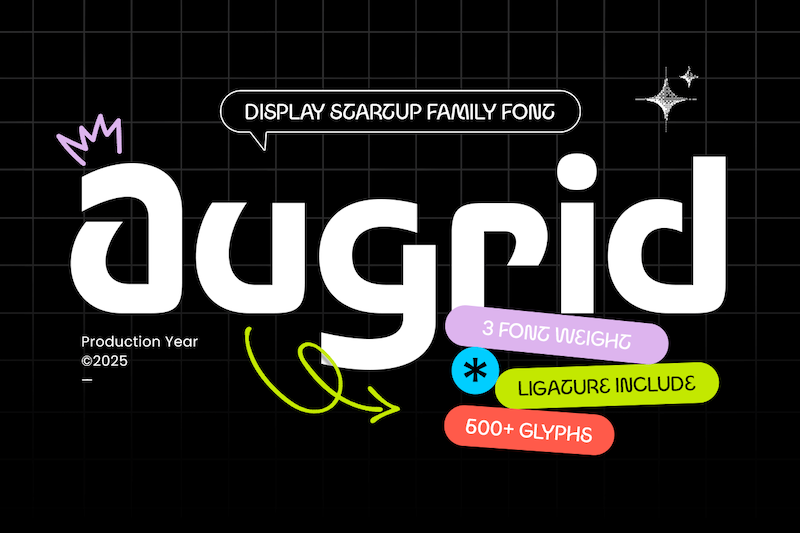
آگرید، یک خانواده فونت لوگوی مینیمال است که طراحی شده تا سادگی، تعادل و ظرافت را به پروژههای برندسازی شما بیاورد. این خانواده تایپفیس که با اشکال هندسی تمیز و تناسبات دقیق خلق شده، برای برندهای مدرن، محصولات دیجیتال و هویتهای بصری جاودانه ایدهآل است.
این فونت برای لوگوها، بستهبندی، هویت سازمانی و طرحبندیهای مجلات و نشریات عالی است و وزنهای متعددی را برای انعطافپذیری ارائه میدهد— از نازک و ظریف گرفته تا ضخیم و با اعتماد به نفس. سبک مینیمال آن، شفافیت و سازگاری را در هر کاربردی افزایش میدهد و آن را به انتخابی برتر برای طراحانی تبدیل میکند که برای سادگی مدرن و هماهنگی بصری ارزش قائلاند.
آگرید با جزئیات تیز و ساختار خوشساخت خود، در هر دو فرمت چاپی و دیجیتال به زیبایی کار میکند و ظاهری حرفهای و صیقلی را برای برندسازی در زمینههای فناوری، معماری یا کسبوکار ارائه میدهد.
خانواده فونت مدرن سنس سریف کامل با وزنهای متعدد.
شامل 3 وزن: نسخه لایت (نازک/روشن)، رگولار (عادی) و بولد (ضخیم).
ایدهآل برای لوگوها، برندسازی، وبسایتها و طرحبندیهای مجلات و نشریات.
طراحی هندسی مینیمال برای ترکیببندیهای تمیز و جاودانه.
به طور یکپارچه در چاپ، بستهبندی و رسانههای دیجیتال کار میکند.
شامل حروف بزرگ، حروف کوچک، اعداد و علائم نگارشی.
دارای ویژگیهای اُپنتایپ برای انعطافپذیری پیشرفته در طراحی.
پشتیبانی چندزبانه.
با آگرید—بهترین خانواده فونت لوگوی مینیمال برای طرحهای مدرن، ظریف و تمیز—برندسازی جاودانه و حرفهای خلق کنید. ✨